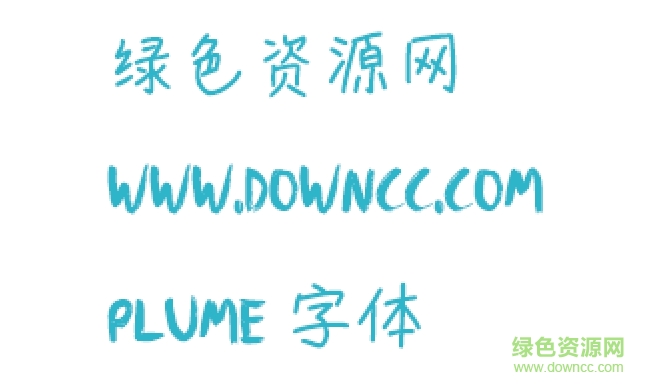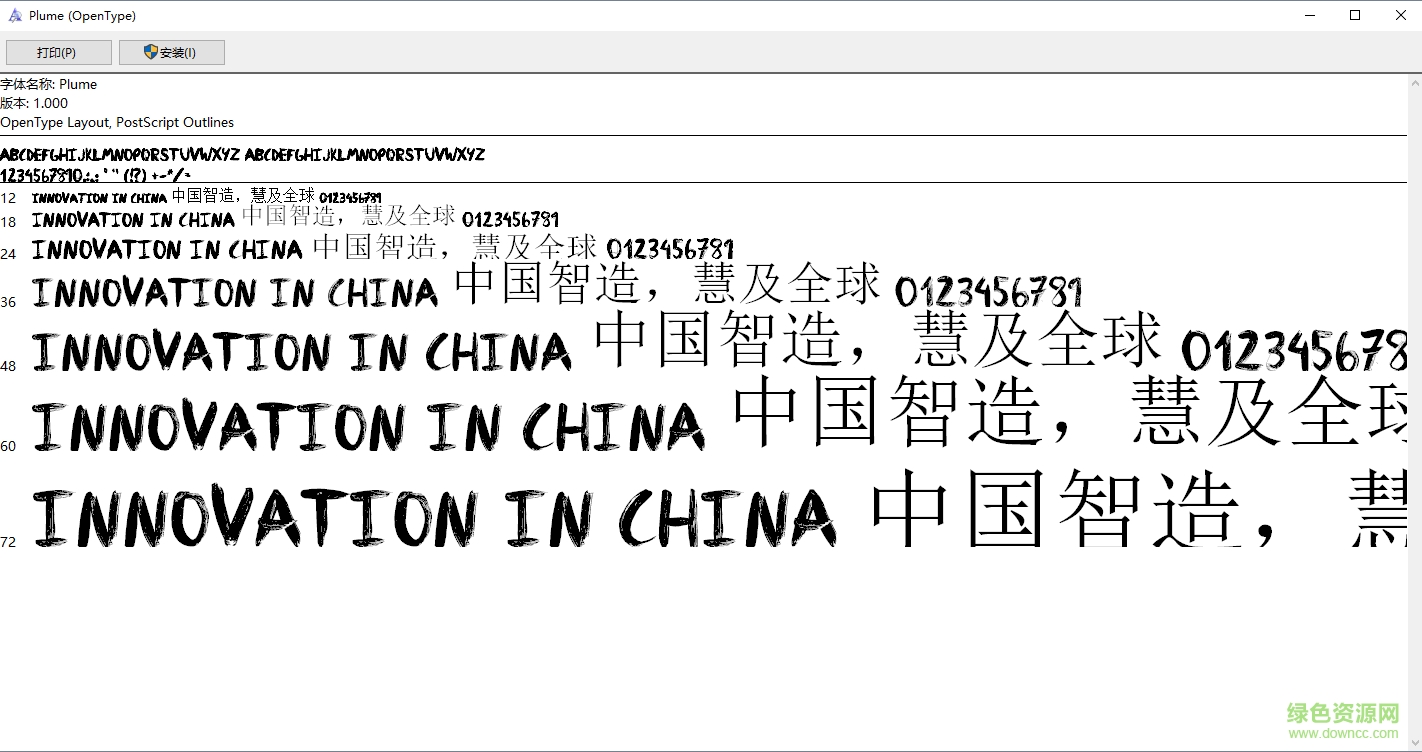
plume字體是一款漂亮的毛筆字體。字體風(fēng)格端正大方,常用于藝術(shù)設(shè)計(jì)。歡迎需要的小伙伴來綠色資源網(wǎng)下載使用。
plume字體是一款非常實(shí)用的中文字體,該字體線條粗細(xì)適中,中文字體端正大方,英文呈毛筆字效果,整體風(fēng)格非常的出色,并且字庫完整,可用于藝術(shù)設(shè)計(jì)、包裝印刷、簽名設(shè)計(jì)、圖形設(shè)計(jì)等領(lǐng)域。
優(yōu)雅美觀,具有禪意